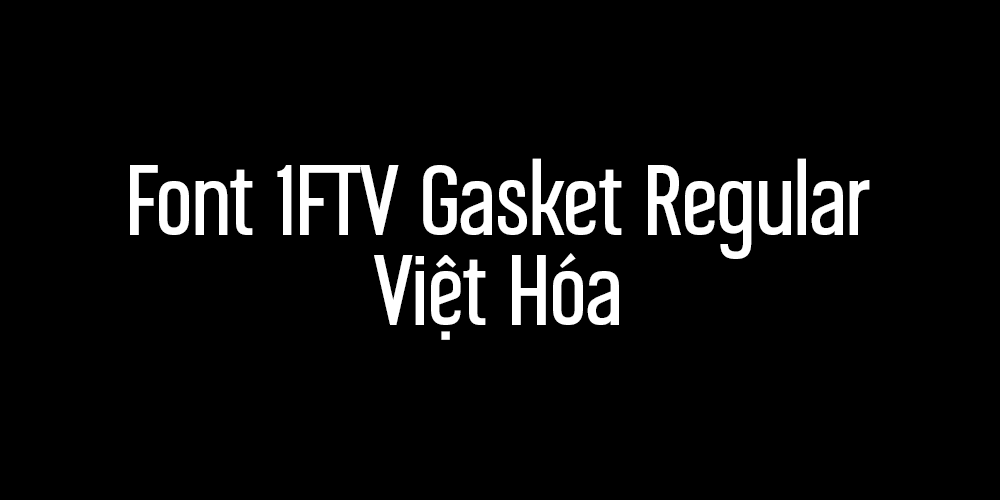
Font 1FTV Gasket Regular
Font 1FTV Gasket Regular là một kiểu chữ độc đáo và sáng tạo, mang đến sự hiện đại và phá cách trong thiết kế. Với những đường nét tinh tế, sắc sảo, mẫu font chữ không chân này thích hợp cho các dự án cần sự nổi bật, cá tính và đậm chất công nghiệp. Được thiết kế với mục đích tạo ra sự khác biệt, Font 1FTV Gasket Regular không chỉ là sự lựa chọn hoàn hảo cho các tiêu đề, logo mà còn lý tưởng để tạo điểm nhấn cho các ấn phẩm truyền thông. Hãy thử nghiệm và cảm nhận sự mạnh mẽ, độc lạ mà font chữ này mang lại cho thiết kế của bạn.